밑줄 긋는 디자이너.10_<그린보이> 외
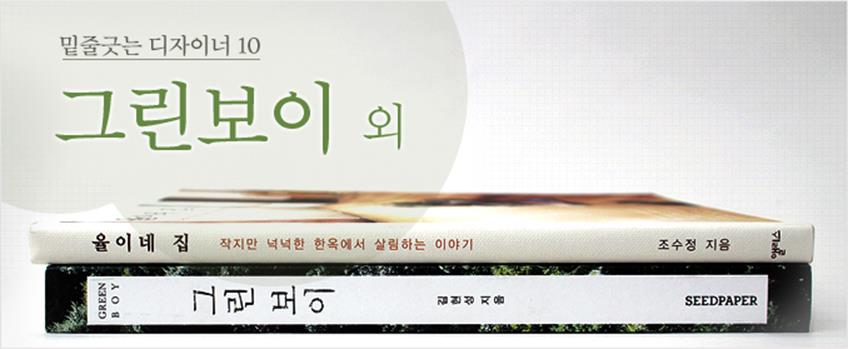
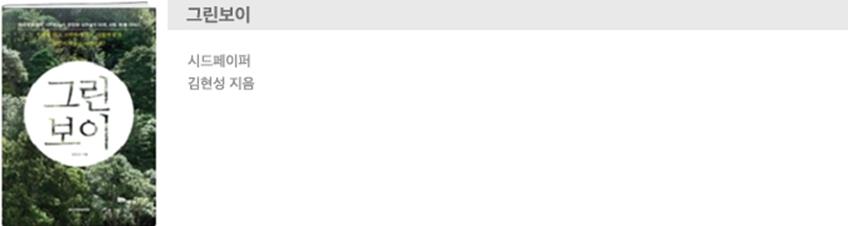
어디서도 볼 수 없는 스타들의 감각적인 패션 화보와 동물, 환경 이야기를 ‘문화’라는 키워드로 쉽게 풀어낸 잡지 <오보이!>. 하지만 배포처를 통해서만 구할 수 있다 보니 읽고 싶어도 구할 수가 없어서 막막했던 독자들이 많았다. 단행본 <그린보이>는 2009년 11월 <오보이!> 창간호부터 2012년 5월 현재 27호까지 그 안에 담긴 김현성의 글과 사진들을 묶고, 못다 한 이야기들을 담아 좀 더 촘촘하게 엮어낸 책이다. 자연과 사람과 동물이 더불어 사는 지구를 만들기 위한 방법들을 여덟 가지 큰 이야기들로 풀어내 다양한 관점에서 접근할 수 있다.
패션에 관심 있는 독자라면 지구도 지키면서 자신도 함께 멋있어질 수 있는 Best shopping means smart shopping(현명한 소비) 챕터를, 채식에 도전해 보고 싶었던 독자라면 Natural foods makes you(채식) 챕터를, 유기동물에 관심 있던 독자라면 Give your heart to animal(동물복지) 챕터를, LP의 아날로그를 그리워하는 독자라면 Once upon a time(아날로그) 챕터를, 그 동안 <오보이!>에 나왔던 화보와 인터뷰를 보고 싶은 독자라면 Your story(사람) 챕터를 읽으면 된다. <오보이!>를 좋아했던 독자에게는 종합 선물세트가 되고, <오보이!>를 몰랐던 독자들에게는 일상의 소중함을 깨닫는 계기가 될 것이다.
“나는 동물을 사랑하는 패션 포토그래퍼입니다. 정확히 말하면 동물을 사랑하면서 과장된 환상의 창조로 소비자를 현혹하고 소비를 부추기는 패션 포토그래퍼죠. 동물을 사랑하는 내가 동물복지와 환경에 신경 쓰면서 패션 포토그래퍼로 살아간다는 건 참 힘든 일입니다. 사진으로 먹고 살지만, 내가 추구하는 것과는 너무나 이질적인 일들을 많이 해야 하는 내 직업은 종종 날 회의감과 무력감에 빠져들게 하니까요.” – 29쪽
“<그린보이>를 만들면서 내가 했던 가장 큰 고민은, 이 책을 만듦으로 인해 베어질 나무와 낭비될 수많은 에너지, 그로 인해 망가질 지구였습니다. 하지만 이 책을 통해 내가 전하고자 하는 메시지를 더 많은 사람들에게 전달할 수 있다면, 좀 더 나은 세상을 만들 수 있을 거라는 믿음으로 책을 만들기로 했습니다. 그리고 이 책을 만드는 취지와 담긴 내용에 부합하는 실천으로, 이왕이면 친환경적인 책을 만들자고 생각했습니다.” – 11쪽
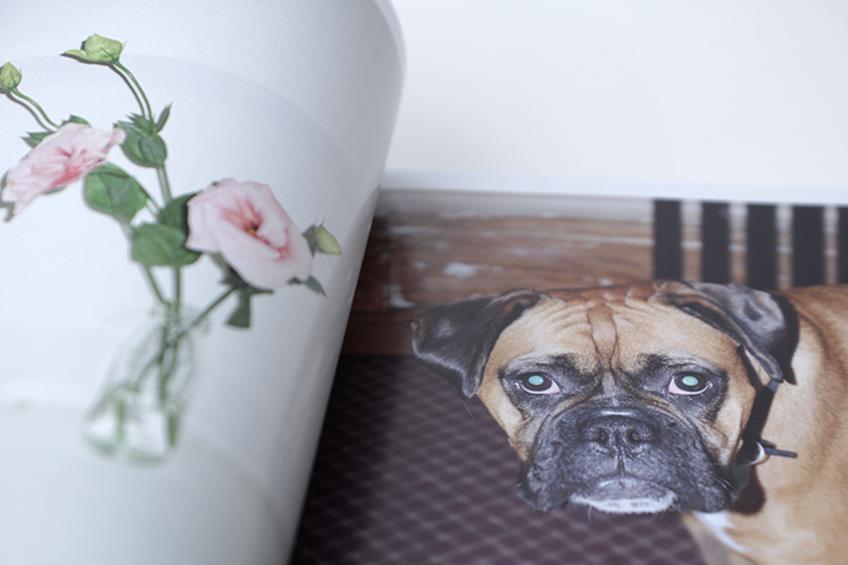
<그린보이>는 책을 만드는 제작 과정에서부터 독자들과의 소통을 위해 고민한 책이다. 독자들에게 일방적으로 친환경을 강조하기보다는, 독자들이 직접 책을 읽으면서 즐겁게 친환경을 경험하고 그 장단점을 느낄 수 있도록 만들어졌다. 세 가지 종이를 사용하여 일반종이와 재생종이를 직접 비교할 수 있게 구성했고, 구멍이 송송 뚫려 있는 에코폰트를 활용해 잉크 절약과 동시에 책에 재미를 주었다. 또한 표지에 어떠한 가공도 하지 않아 나만의 손때가 묻어가는 종이책 본연의 아날로그 감성을 느낄 수 있도록 했다.
환경보호나 동물복지에 대해 이야기하는 책은 많다. 하지만 이런 내용들은 우리가 실천해야 하는 좋은 이야기인 것은 맞지만, 사람들이 읽기에 지루하거나 고리타분하게 느껴질 수 있다. 이러한 한계를 극복하고 사람들의 관심을 환기시키기 위해 <오보이!>가 선택한 것이 스타들의 패션 화보라면, <그린보이>에서는 패션계의 러브콜을 한 몸에 받는 패션 포토그래퍼 김현성 특유의 감각적인 사진으로 보는 즐거움을 더하고, 딱딱하고 이해하기 어려운 통계 자료들을 쉽게 풀어내는 방식을 택했다. 쉽고 편안하게 읽을 수 있는 책이지만 이 책이 담고 있는 메시지만큼은 결코 가볍지 않다는 것! 믿는 바를 분명하게, 그러나 부드러운 방법으로 자연스레 이야기하는 책이다.
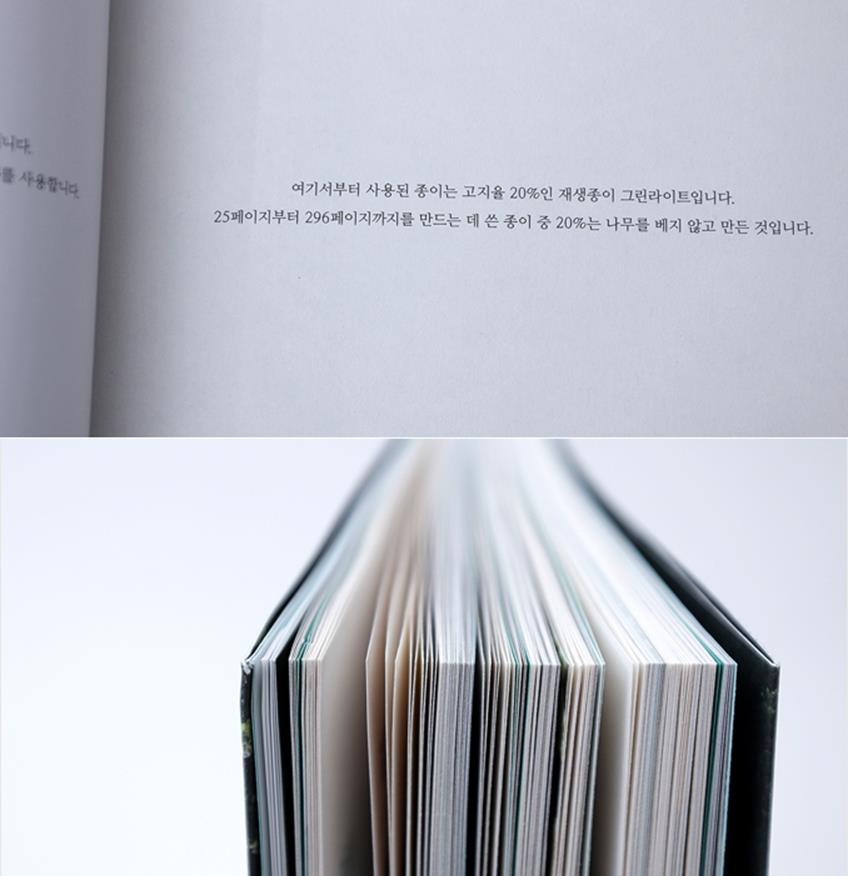
“환경이 그러게 중요한가요?”
“먹고 살기 바쁜데 너무 사치스러운 생각 아닐까요?”
“다들 슬로라이프를 얘기하는데, 어떻게 시작해야 하나요?”
“안 그래도 신경 쓸 게 너무 많은데, 복잡하지 않나요?”
너무 어렵고 부담스럽게 생각하지 마세요. 슬로라이프는 꼭 뭔가를 실천하고 행동으로 옮겨야 하는 게 아니라 작은 생각의 변화로부터 시작되니까요. 내일 집으로 돌아올 때 한 정거장 일찍 내려서 천천히 걸어 보는 건 어때요? 슬로라이프가 시작되면 건강한 인생이 시작됩니다. – 93쪽
“아날로그는 추억입니다. LP는 현재의 아날로그입니다. 아이팟은 미래의 아날로그입니다. 아날로그는 지친 현대인들의 감성을 자극하는 선물입니다. 낡은 것은 버릴 것이 아니라 지키고 가꿔야 할 무엇입니다. 가끔은 뒤도 한 번씩 돌아보세요.” – 257쪽
“이 책은 각박하고 정신없는 요즘 세상에서 자신을 돌아보고 한 걸음 뒤로 물러나 객관적으로 인생을 점검하는 책입니다. 조금 더 느리고 조금 더 의미 있는 생활을 통해 자연과 사람과 동물이 어우러져 살 수 있는, 지구에 한 걸음 더 다가가기 위한 메시지를 담았습니다. 무엇을 할 것인가가 아니라 무엇을 하지 않을 것인가에 관한 이야기입니다. 오늘도 꽉 막히는 도로 위의 자동차에 혼자 앉아서 다른 자동차들을 원망하고 있을 누군가를 위한 위로입니다. 쏟아지는 인터넷 정보의 홍수 속에서 잠시 빠져 나와도 뒤지지 않을 거라는 이상무 신호입니다. 느리게 살면 인생도 천천히 간다는 단순한 명제입니다.” – 6쪽
그는 책 속에 ‘자연을 지키기 위해서 이렇게 해야 하고, 동물을 지키기 위해서 이렇게 해야 한다’가 아니라, 사람 스스로 의미 있는 삶을 살기 위해 어떤 것들을 고민하고 실천해야 하는지에 대한 이야기를 담았다. <그린보이>는 정신 없이 바쁘게 돌아가는 세상에서 잠시 멈춰 서서 자신의 삶을 돌아보고, 진정 의미 있는 삶이 무엇인지, 이타적인 삶의 즐거움을 배울 수 있는 방법들을 알려 주는 책이 될 것이다.
김현성
동물을 사랑하는 패션 포토그래퍼. 밤식이와 먹물이, 그리고 뭉치의 아빠. 환경과 동물을 생각하는 패션 문화잡지 「Oh Boy!」의 발행인이자 편집장. 017 번호의 2G 휴대폰을 쓰고, 아이팟보다는 LP가 좋다는 구닥다리 아저씨. 알수록 힘들지만 할수록 즐겁다는 채식주의자. 유행을 좇지 않아도 베이직하게 멋진 남자. 미스코리아도 아닌데 세계 평화가 소원인, 자연과 사람과 동물이 더불어 사는 작은 별 지구를 꿈꾸는 사람.
20세기에 들어 비약적인 경제성장이 이뤄지면서 그 속에서의 주거 양식 또한 서구적 형태로 규격화, 획일화되었다. 최근에는 주거문화에 대한 패러다임과 라이프스타일의 변화로 인해 주거 트렌드가 급속도로 변하고 있긴 하지만, 그 속에서도 ‘한옥집’은 여전히 옛 것이라는 과거의 형태로 남아 찾아보기 쉽지 않다. 자연친화적이며 고즈넉하고 정겨운 분위기라는 장점이 있지만 불편한 점도 신경 써야 할 점도 많아 다소 까다롭다는 단점 또한 공존하기 때문일 것이다. 이 책의 주인공인 율이네 집은 바로 통의동에 위치한 작은 한옥집이다.
책 속에 있는 집과 사진이 예뻐 읽게 되었는데, 알고 보니 저자는 문구 브랜드 ‘공책(O-CHECK)’을 만든 디자이너였다. 개인적으로 고등학교 시절부터 공책이란 브랜드를 애호하고 애용해 왔던지라 이런 제품을 만드는 사람들이 어떤 모습인지 궁금했었는데, 책을 읽고 나니 그 제품들이 소박한 한옥집에서 천천히 흐르는 삶을 살아가는 그들과 많이 닮아있다는 것을 느낄 수 있었다.
“매일 눈을 뜨면 마주하는 삭막한 콘크리트 벽, 네모난 전철 안에서의 부대낌, 열리지 않는 창이 빼곡하게 박힌 빌딩 속에서 우리의 일상과 말이 어색하고 딱딱하고 뾰족해진 게 아닐까. 공간의 생김이 어느새 인간의 삶을 빚어내고 있는 건 아닌지…” – 6쪽
“더 좋은 것, 더 빠른 것, 가장 최신의 것만을 이야기하는 세상에서 조금 느려도 괜찮고, 새 것이 아니어도 좋아. 라고 말할 수 있는 넉넉한 마음을 품게 해준 한옥집 이야기를 들려주려 한다.” – 7쪽
빠르게 돌아가는 세상 속에서 뒤쳐지지 않기 위해 급하게 달려가던 스무 살 무렵의 여자아이는 어느 벚꽃 흩날리는 봄날에 찾아간 선생님의 한옥집에서 다감한 위로를 받게 된다. 하늘과 처마 끝, 단정한 장독대, 바람에 가늘게 떠는 문풍지 소리… 소박하고 오래된 것에서 나오는 조용하고 따스한 바람. 율이네 가족이 지금의 이 작은 한옥집을 만나게 된 것은 그날의 짙은 여운 때문이었을지도 모른다.
율이네는 이사 전 집을 고치는 과정을 거치면서 뭔가 거창한 의식과도 같은 비움의 시간을 가졌다고 한다. 가지고 갈 수 없는 가구와 짐을 정리하였고, 담백한 벽과 나무 기둥 등은 이미 자기만의 빛깔을 내고 있었으므로 고급 마감재나 가구, 세련된 벽지들은 그야말로 쓸모 없는 덧칠이라는 것을 깨달았다. 그들은 세월의 흔적을 그대로 간직하고 있는 집의 모습을 최대한 유지하면서 반드시 보수가 필요한 부분만 고쳐나가기 시작했다.
책을 통해 한옥집에서 연출할 수 있는 소소하지만 센스있는 인테리어 팁이나, 소품 제작, 공간 활용에 대한 정보도 엿볼 수 있다. 연애시절부터 끊임없이 무언가를 만들고, 판매하는 일을 좋아했던 부부는 버려진 문짝이나 창문 등을 멋스러운 테이블과 수납장으로 변신시키고, 정겨운 나무 그릇과 질 그릇에 마당에서 직접 재배한 채소로 소박한 밥상을 차리고, 한땀한땀 정성스럽게 만든 앞치마, 쿠션, 방석, 커튼 등을 집 안 구석구석에 두어 작은 부분까지 빛나게 한다.
소파 없는 한옥의 마루에 모여 앉아 고구마를 먹는 일, 율이와 나란히 누워 책을 읽는 일, 마당에서 불어 온 바람, 비 오는 날 마당 그득히 퍼지는 향긋한 풀냄새, 햇살 담은 뽀송뽀송 빨래 냄새가 담겨 있는 책. 요리를 즐기는 아빠가 스파게티를 만들면 율이는 마당에 있는 바질을 따오고, 샐러드를 만들 때면 야채의 물기를 빼는 일을 도맡아 하는 율이. 율이는 이런 시간을 통해 자신이 가족의 일원으로 무언가를 하고 있다는 것에 큰 의미를 두고 자랑스러워한다고 한다.
어느 날 마당에서 무언가를 한참 생각하던 율이가 내게 말했다.
“엄마, 나는 한옥으로 이사와서 참 좋아. 기와지붕이 정말 예쁜 것 같아. 마당에서 뛰어 놀아도 되고, 매일 하늘도 볼 수 있잖아.”
율이네 가족의 손길과 온기로, 세월이 흐르면서 더욱 그들의 모습을 닮아갈 한옥집.
그리고 그런 한옥집처럼 느리고 향기로운 삶을 살아갈 그들을 보며
나 또한 훗날 이런 곳에서 살 날을 꿈꾸어 본다.
조수정
대학에서 의상학을 공부하고 오브제/오즈세컨과 쌈지에서 비주얼 머천다이저로 일했다. 그러다 2000년 12월 남편과 함께 손맛이 살아 있는 디자인 문구 브랜드 ‘공책 디자인 그래픽스(O-CHECK DESIGN GRAPHICS)’를 만들었다. 쓸모 있는 물건 못지않게 마음에 필요한 물건들의 소중함을 아는 그녀는 문구 브랜드 공책을 확장해, 리빙 디자인 회사 ‘스프링 컴 레인 폴(SPRING COME, RAIN FALLl)’을 남편과 함께 설립하여 현재 디자인 실장으로 일하고 있다. 요리하는 남편과 자전거 타는 아들이 보이는 마루에서 예쁜 소품을 만드는 시간이 가장 행복하다며, 천천히 흐르는 삶의 소중함을 알려준 한옥이 너무 고맙다고 이야기한다.